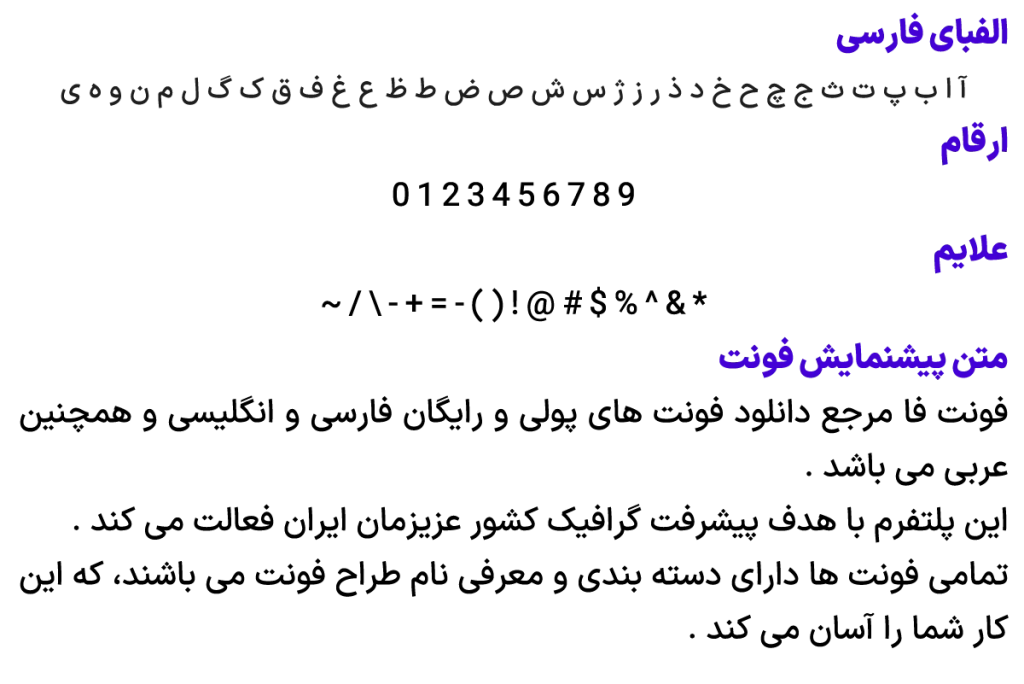
پیشنمایش فونت ایران سنس
فونت فارسی ایران سنس - IranSansX
توضیحات و معرفی فونت ایران سنس
فونت فارسی ایران سنس ( IranSansX ) از مجموعه فونت های آزاد می باشد، همچنان نوع فونت طراحی وب و عنوان و متن می باشد.
فونت شگفت انگیز و زیبای فوق توسط مسلم ابراهیمی در سال 1393 از روی خط نسخ طراحی و ساخته شده است.
فونت معرفی شده یکی از پرطرفدارترین قلم های ایرانی در چند سال گذشته می باشد .
همچنان فونت ایران سنس در 11 وزن سنگین و پر رنگ و نیمه پر رنگ و فوق العاده سنگین و فوق العاده پررنگ و حروف سنگین و سبک و متوسط و معمولی و نازک و فوق سبک است.
در لیست زیر می توانید وزن های این فونت شگفت انگیز و زیبا را ببینید.
وزن های فونت IranSansX
داستان نامه ایران‌سنس
زمانی که بوم سازگان کسب و کارهای ایرانی در حال رشد و موفقیت بودند، این فونت اولین بار در سال 1393 منتشر شد.
طراح رابط کاربرانی که در این شرکت ها کار می کردند، برای اولین بار از این فونت زیبا استفاده کردند.
این فونت در سایت هایی مانند دیجیکالا، کافه بازار، آپارات، اسنپ و … برای نخستین بار مورد استفاده قرار گرفت.
این شد که این فونت به یکی از پربازدیدترین و محبوب ترین فونت ها در قلب کاربران و طراحان ایرانی جای گرفت.
وریبل فونت، چینش دقیق نقطه ها و دندانه ها، تغییر تراز عمودی اعداد و حروف جایگزین از مهم ترین ویژگی های فونت مربوطه است.
در ادامه شما می توانید عکس زیر ببینید که توسط فونت ایران سنس نگارش و طراحی شده است.
فونت فارسی ایران سنس - IranSansX
همانطور که می بینید شعر نام جاوید وطن در قالب یک عکس و فونت iransans خیلی زیباست.